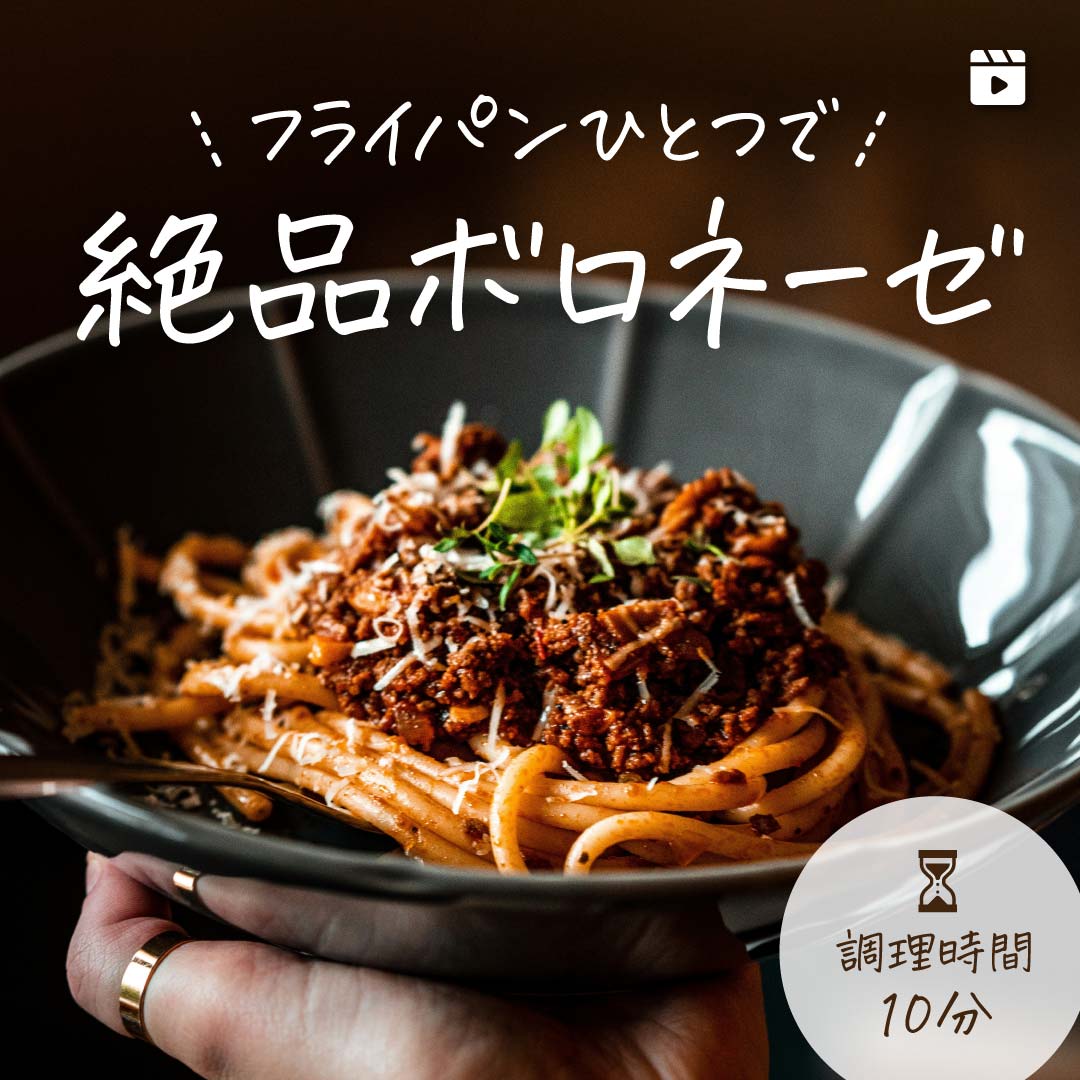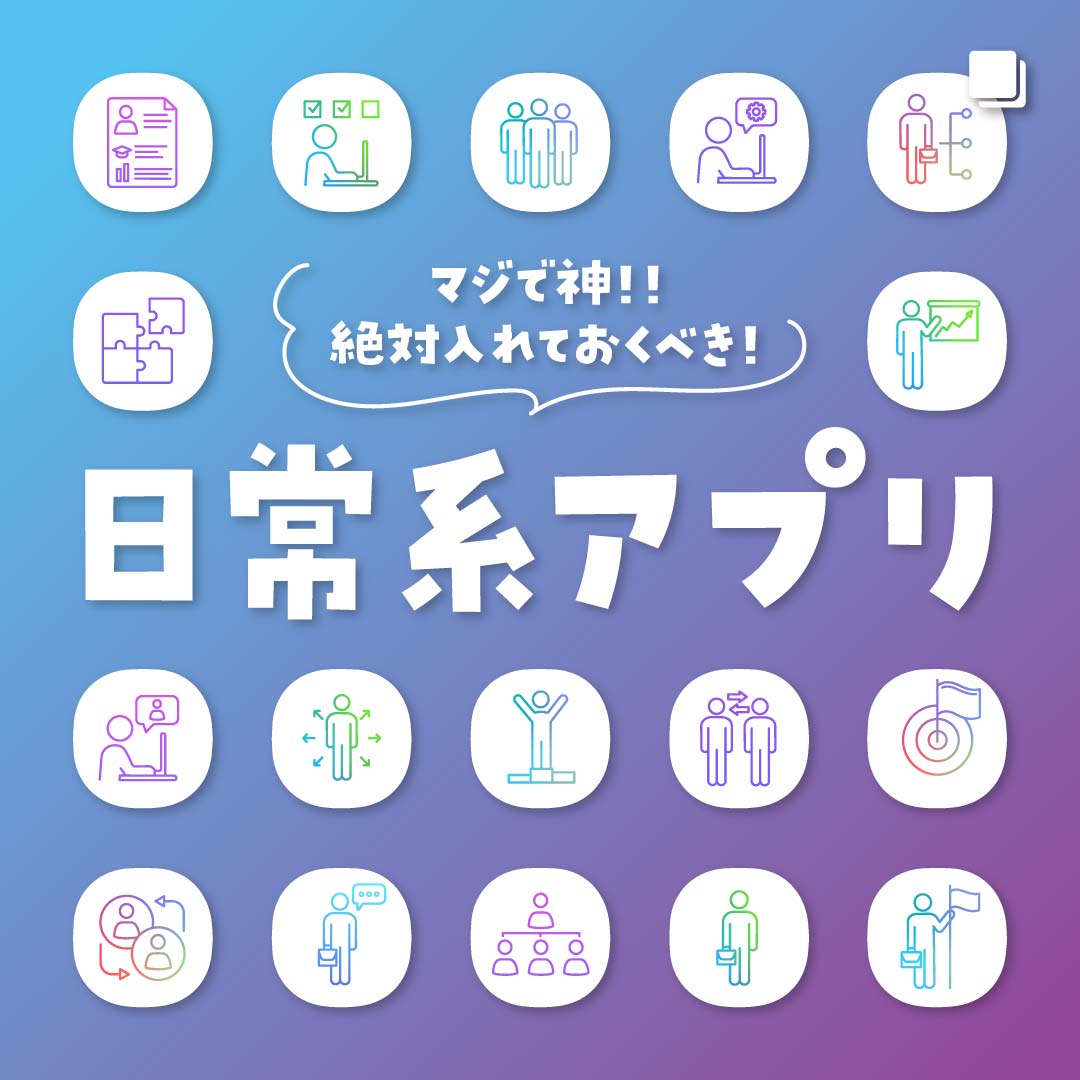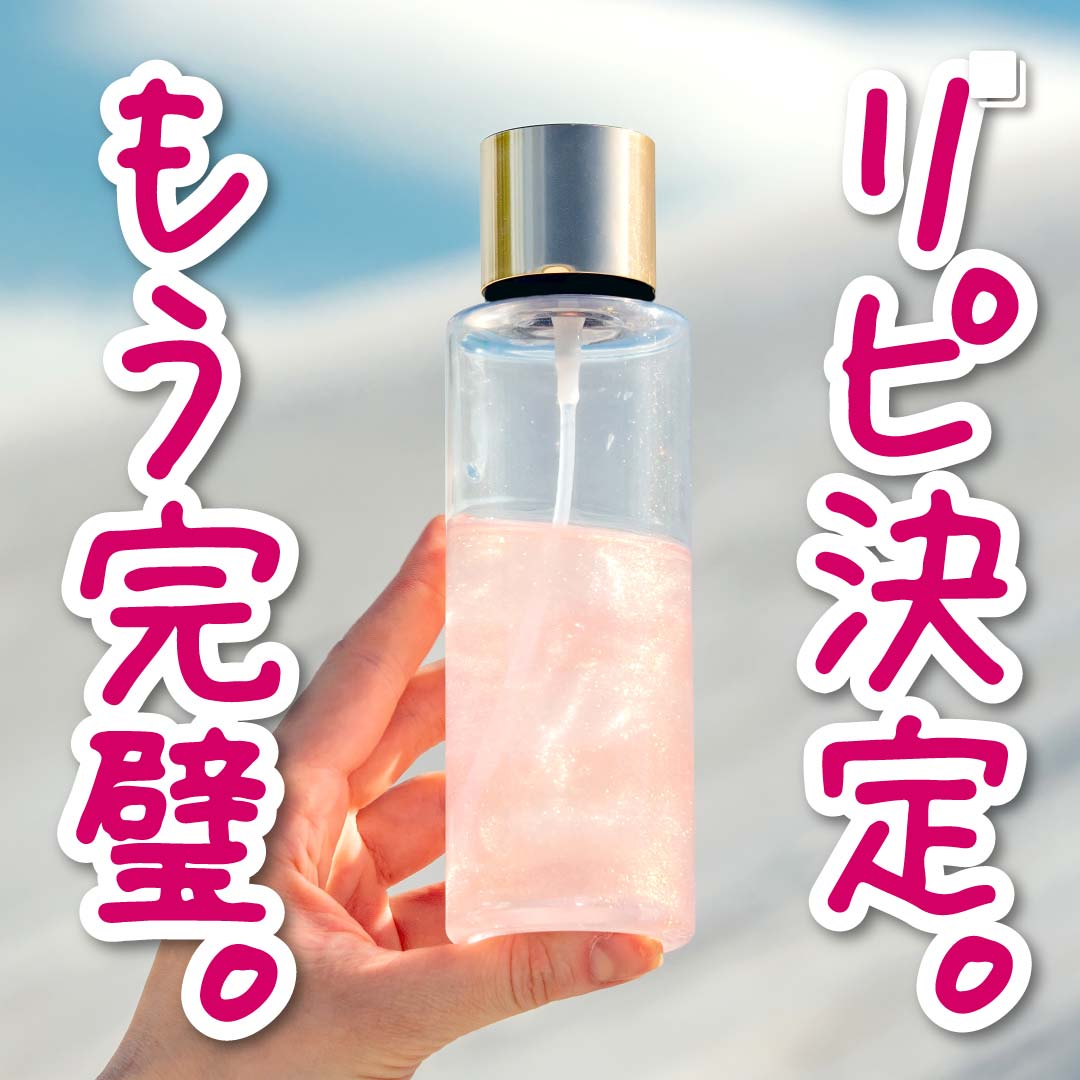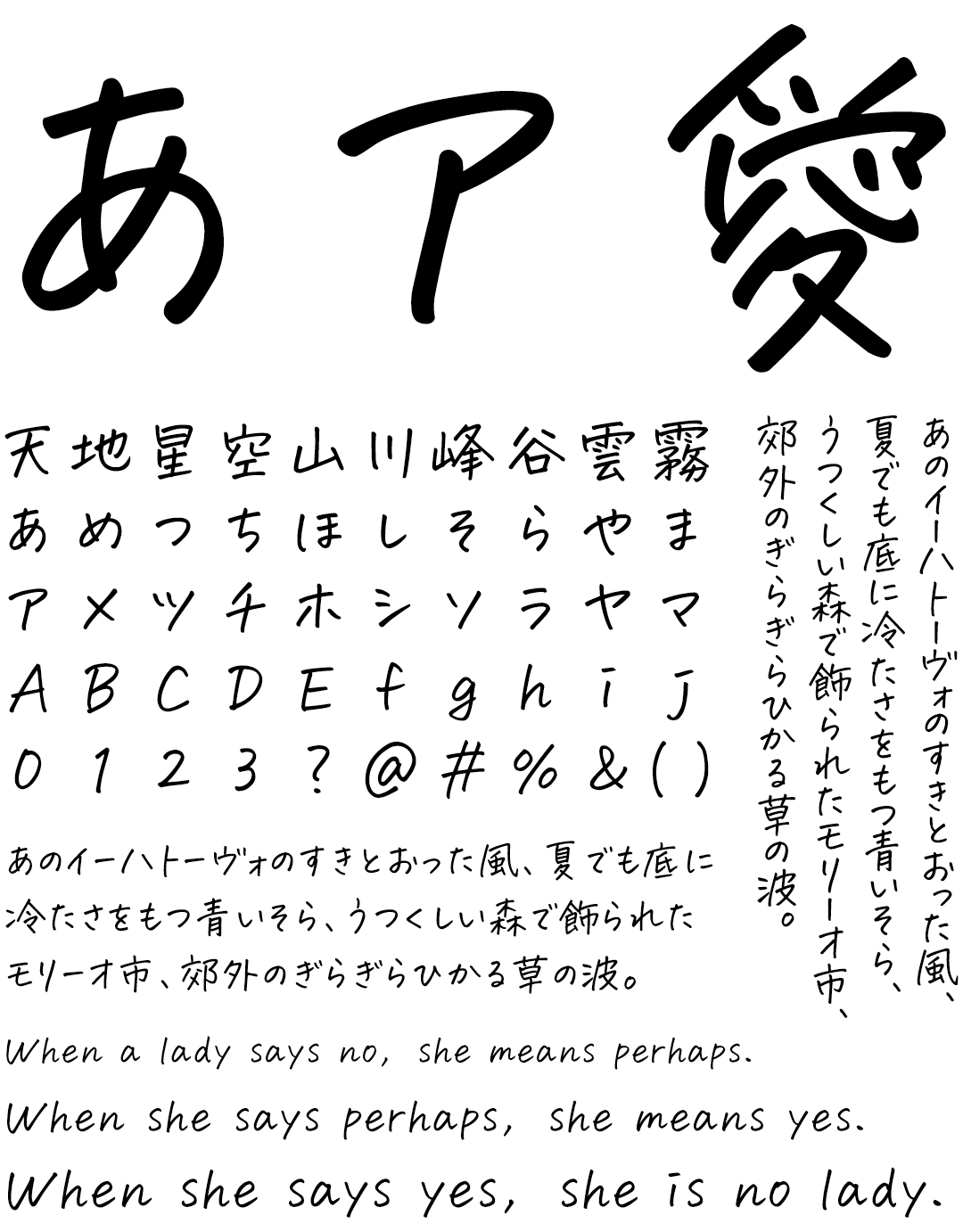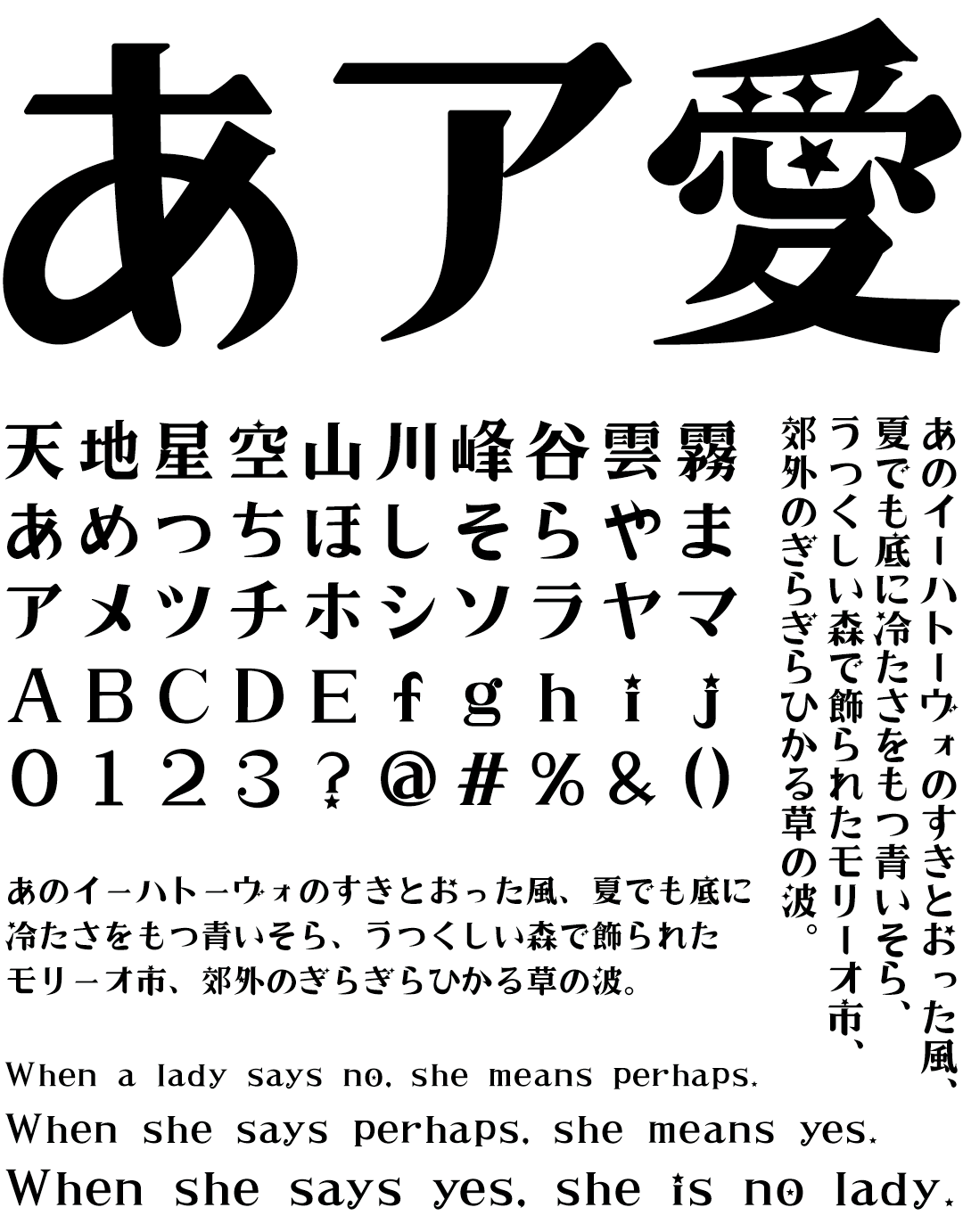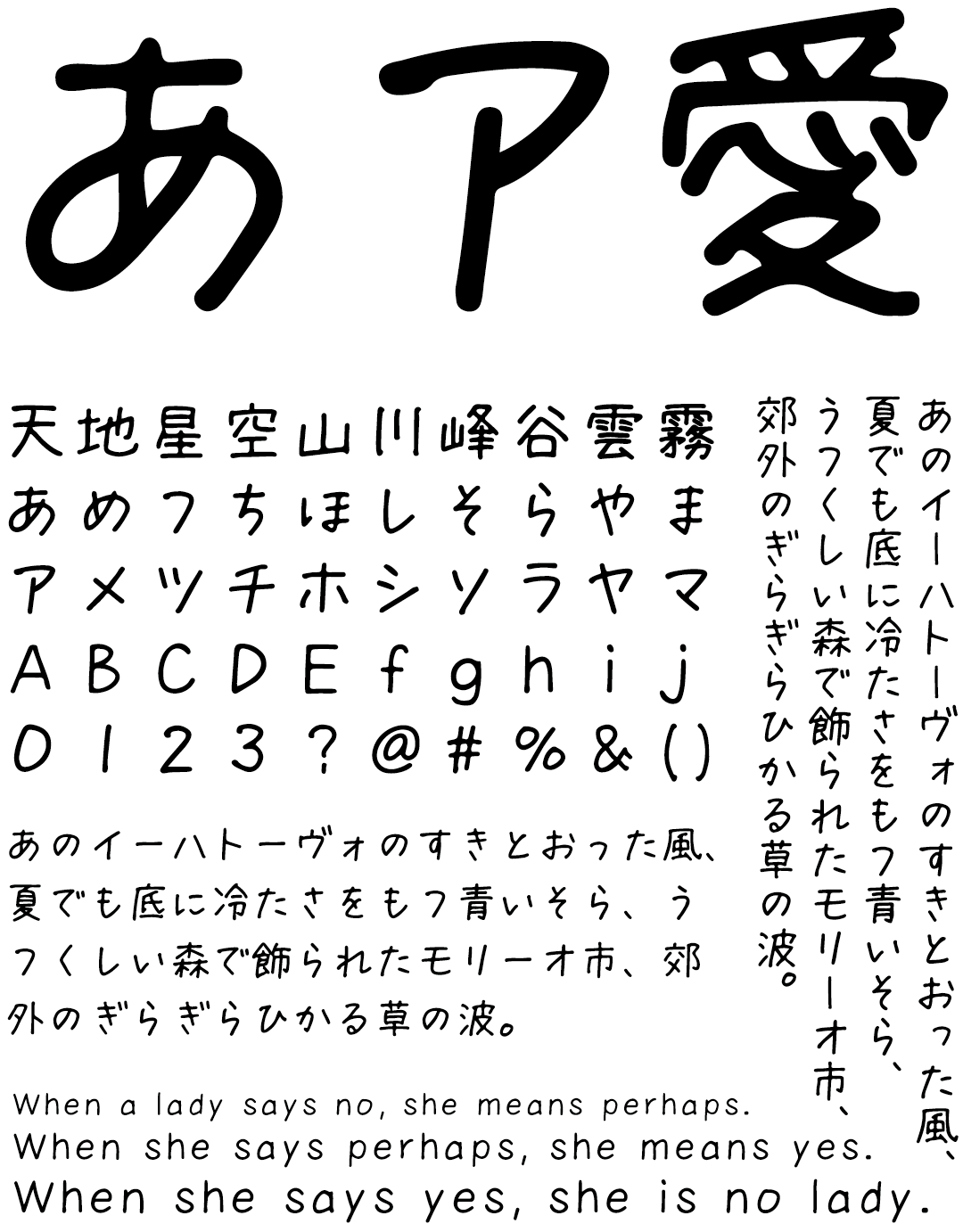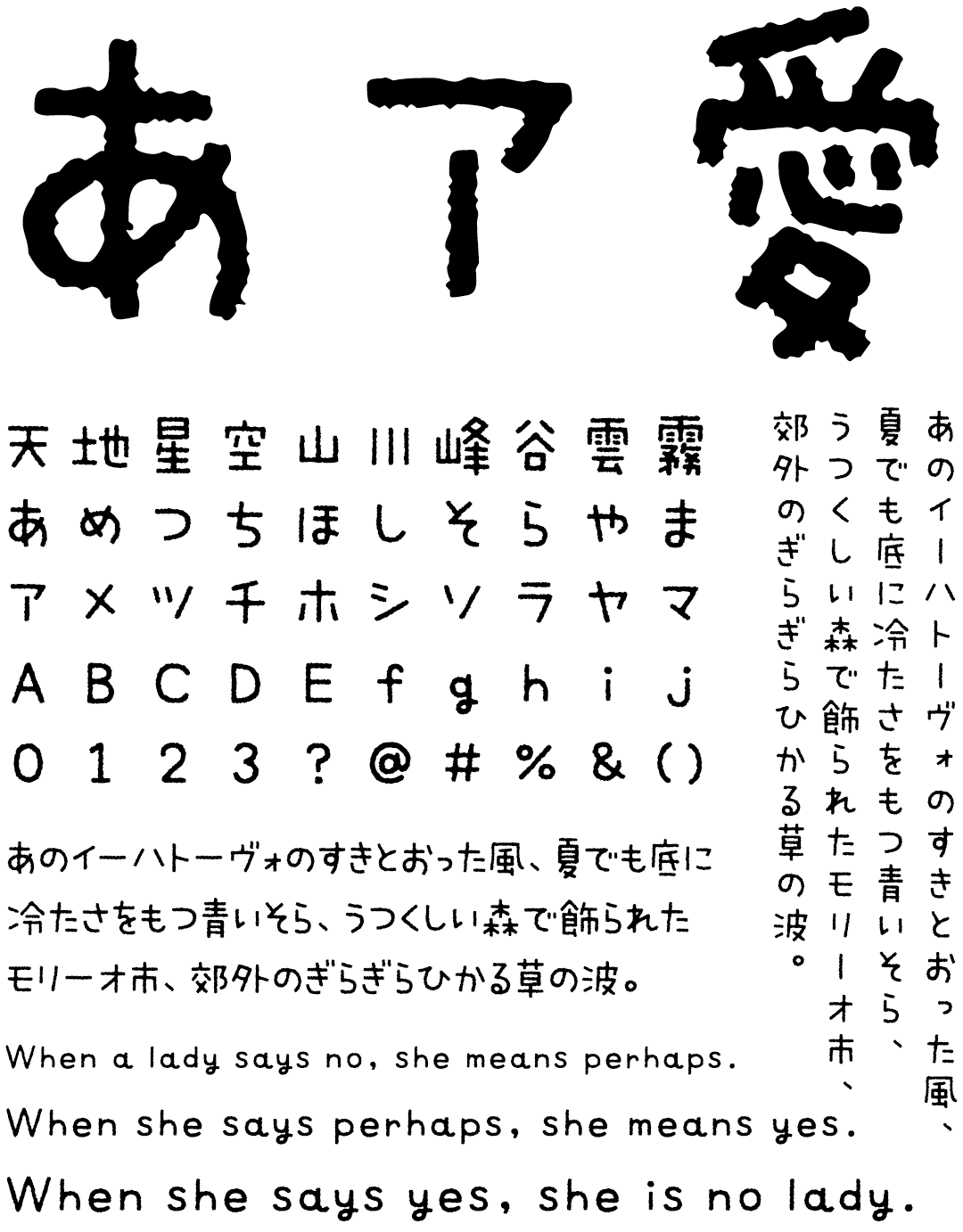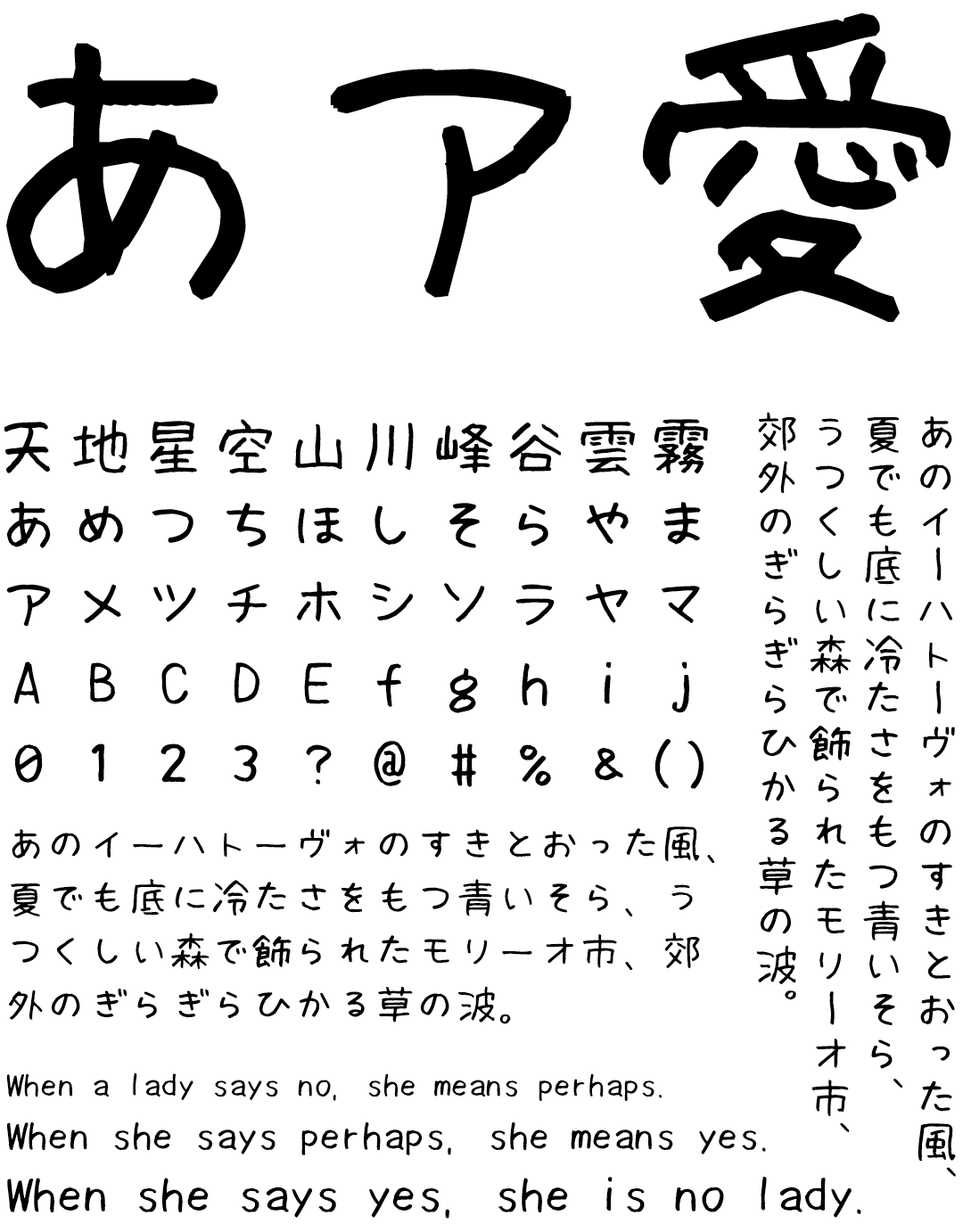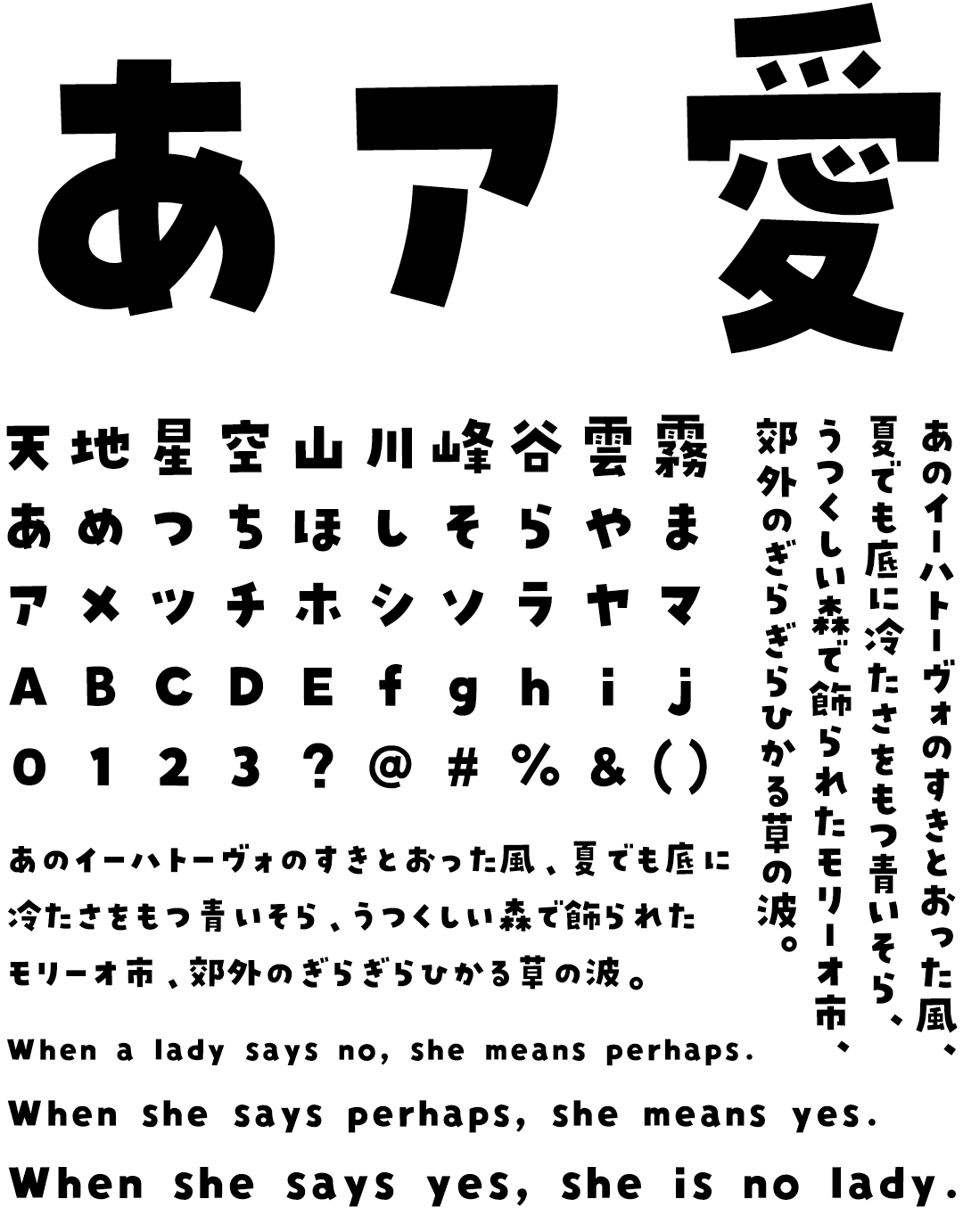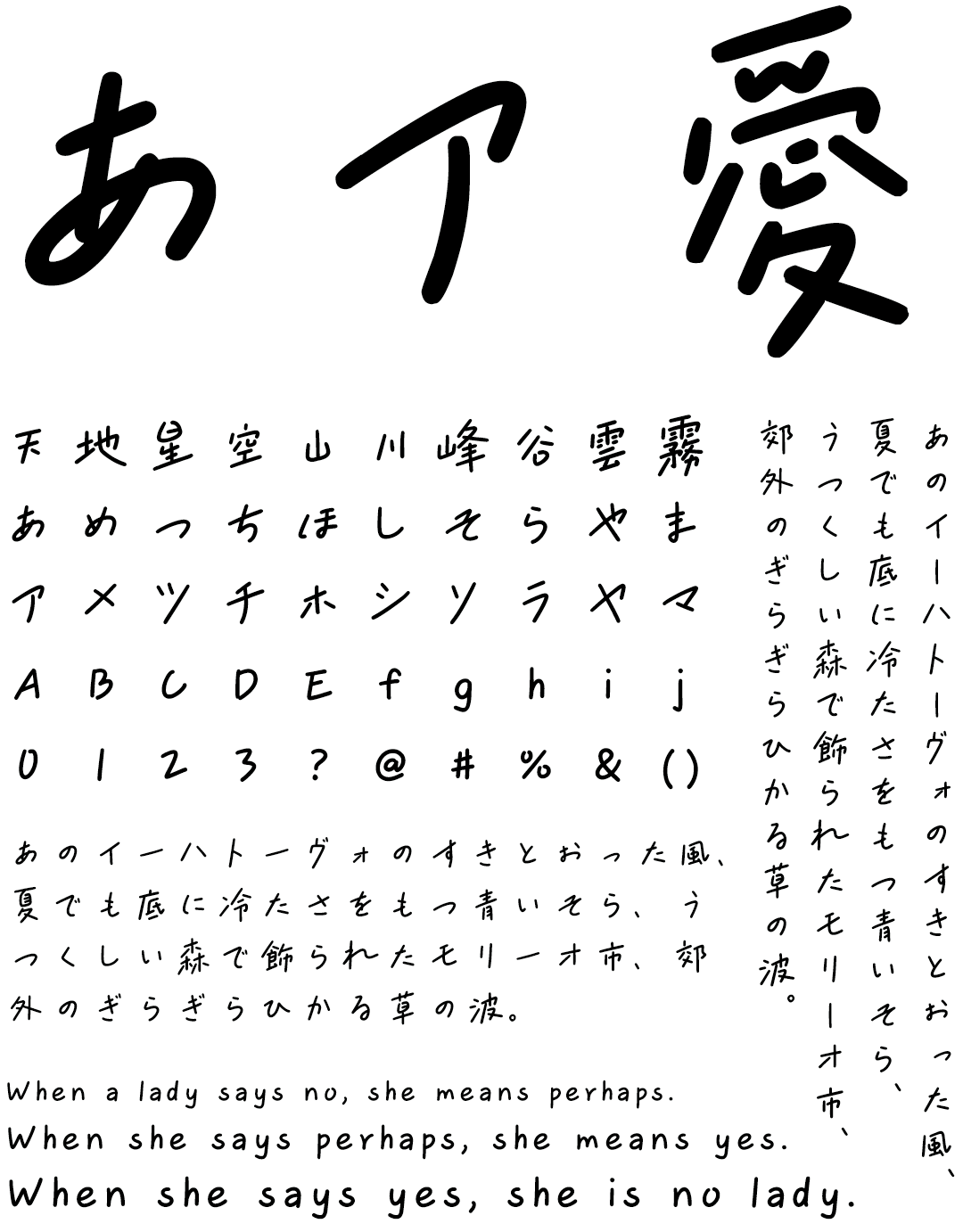
見られているのは「写真」だけじゃない。フォントが変わると、伝わり方が変わる。
Instagramにぴったりなフォント特集|共感・感情が伝わる書体を厳選
Instagramの投稿で印象を決めるのは、写真だけではありません。投稿に添える“ひと言”こそが、共感や保存の決め手になることも。
OSやMS Officeにバンドルされたフォントや無料フォントでは他者と被ってしまう、似たり寄ったりな投稿に差をつけるなら、“フォント選び”が重要。
「いいね」「保存」が増える、手書き風フォントやガーリー、ナチュラル系の書体など、Instagramで想いを伝える・世界観をつくるためのフォントをご紹介します。
趣味の発信にも、ブランドの発信にも、「らしさ」を表現して伝わる投稿に変える“選ばれるフォント”で、あなたの投稿をもっと伝わるものに。
なぜ、Instagramの投稿に“フォント”が大事なの?
ヒラギノ角ゴ 比較サンプル
ヒラギノ角ゴ
iPhoneの日本語表示用標準フォント
パンダベーカリー 比較サンプル
パンダベーカリー
文字が目に留まり、可愛さや遊び心が伝わる
花とちょうちょ 比較サンプル
花とちょうちょ
感情や世界観が一目で伝わり共感されやすい
Instagramでは、写真に添える「ひと言」が投稿の印象を大きく左右します。
多くの人が使う無料フォントは便利ですが、かぶりやすく、どこか無難な印象に。
それに対して、有料フォントは書体そのものに世界観があり、感情やニュアンスが一目で伝わります。
同じ言葉でも、手書き風やデザインフォントに変えるだけで、「あ、いいな」と思わせる力が生まれます。
「伝わる投稿」に変えるには、まず“文字の表情”を変えることから。
無料では出せない、あなただけの伝え方がここにあります。
投稿イメージで見る Instagramにぴったりなフォント
Instagramにぴったりなフォント 厳選15書体の詳細をご紹介
Instagram 情報・ノウハウ系にぴったりなフォント
情報を簡潔かつ視覚的に伝える投稿に最適です。整ったレイアウトと高い可読性により、図解や解説系のコンテンツに信頼感を与えてくれます。
花とちょうちょ
直線的で読みやすい構造を持ち、図解や豆知識など視認性が重視される投稿に最適です。
まっすぐで視認性の高い字形が、スマホ上での情報コンテンツをストレスなく読ませてくれます。
花とちょうちょ
SNSで話題沸騰中の大注目のフォントです。ペンで右上がりに書いた手書き文字から作った、ちょうちょのように軽やかな日本語フォントです。
パンダベーカリー
安定感のあるベースラインとクセのない字形が、情報を簡潔に伝えたい投稿にフィットします。
図やアイコンとの組み合わせに向いており、知識系コンテンツに整然とした印象を加えます。
パンダベーカリー
SNSでも話題の大人気フォントです。手描きのような自然なリズム感と、見出しやパッケージにも最適なしっかりとした太さ。そして何より手作り感のある可愛らしさ。
まちのてちょう / まちのてちょう Bold
ニュートラルで整った文字の印象が、投稿の読みやすさとインパクトを演出してくれます。
言葉の一つひとつを丁寧に伝えたい時に、信頼感あるトーンを作ってくれます。
まちのてちょう / まちのてちょう Bold
温かみのある手書きの風合いと高い可読性を兼ね備えたフォントです。背景写真やSNS投稿にも自然に溶け込み、縦書きでも美しく整います。
りいクッキー L/R
紙に書いた文字から作った、楽しいイメージの視認性の高いフォントです。
見出・タイトルから本文まで、あらゆるデザインで使える万能フォントです。
りいクッキー L/R
紙に書いた文字から作った、楽しいイメージのフォント。
どっしりとしたRと、少し細めのL、2ウェイトファミリーです。
タカ草原
優しく飾らぬ手書きの魅力を持つ書体。力の抜けた線やわずかな揺らぎが、ナチュラルな温かみを感じさせます。ラフな可愛さやオシャレ感の演出にポイントとして使いたいフォントです。
タカ草原
草原に吹く爽やかな風、草花が咲き、蝶が舞い鳥のさえずりが聞こえてくる。そんな優しく飾らぬ手書きの魅力を持った書体。
Instagram セルフブランディング・エッセイ系にぴったりなフォント
日常の中の小さな感動や余白を共有する投稿にぴったりです。手書き風の自然な流れが「等身大の自分」を感じさせ、エッセイ系投稿として非常に響きやすくなります。
空とひこうき
ラフな線の中にも整った読みやすさがあり、ナチュラルに気持ちを綴るエッセイに最適です。
文字の線に揺らぎがあり、日常のつぶやきや心の小さな動きをそっと伝えるエッセイ投稿にぴったりです。
空とひこうき
空に長く伸びて行くひこうき雲をイメージした書体で、右上りの勢いとリアルな手書き感が特徴のフォントです。万年筆でさらりと書いたような、はしり書き日本語フォントです。
左利きの彼女
手書き文字のような自然さが魅力で、共感を呼びたい投稿にぴったりの存在です。
言葉の余白を感じさせるゆるやかなフォルムが、直筆のようなリアル感を伝えます。
左利きの彼女
左利きの作者が丁寧に書いた手書き文字をフォントにしました。細くて少し小さい、繊細な印象のフォントです。
星空みんちょう
くせのない書きぶりが、どんな投稿にもすっと溶け込み時々出てくる★がアクセント。
さりげない丸みが、心情をふっと柔らかくしてくれるので、自己開示のような文脈にも最適です。
星空みんちょう
星やキラキラを散りばめ、星空をイメージした手作りの明朝体フォントです。
花とちょうちょ
一文字一文字に個性があり、感情の“にじみ”を視覚的に演出してくれます。
飾らない言葉と相性が良く、静かな投稿にあたたかみを与えてくれます。
花とちょうちょ
SNSで話題沸騰中の大注目のフォントです。ペンで右上がりに書いた手書き文字から作った、ちょうちょのように軽やかな日本語フォントです。